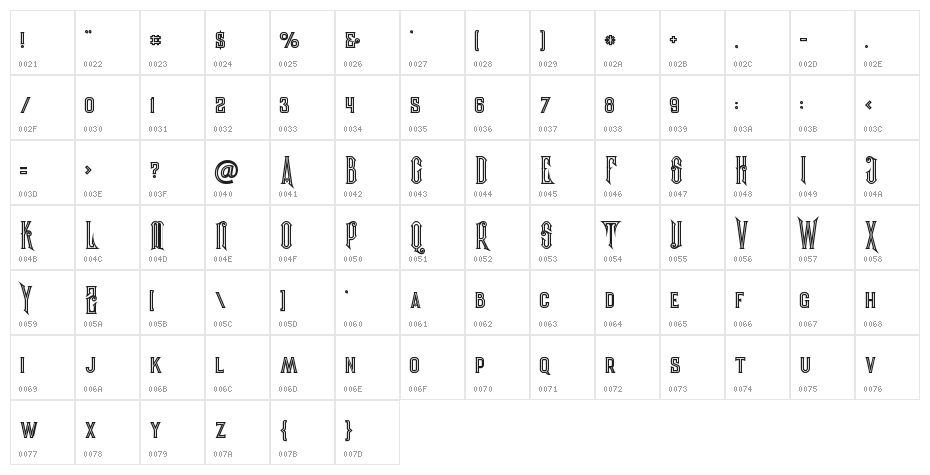
Evolve Inline Font
| Stile generale | Modern Vintage |
| Progetti proposti | This font is perfect for branding, poster design, album covers, and any project that requires a bold, artistic statement. |